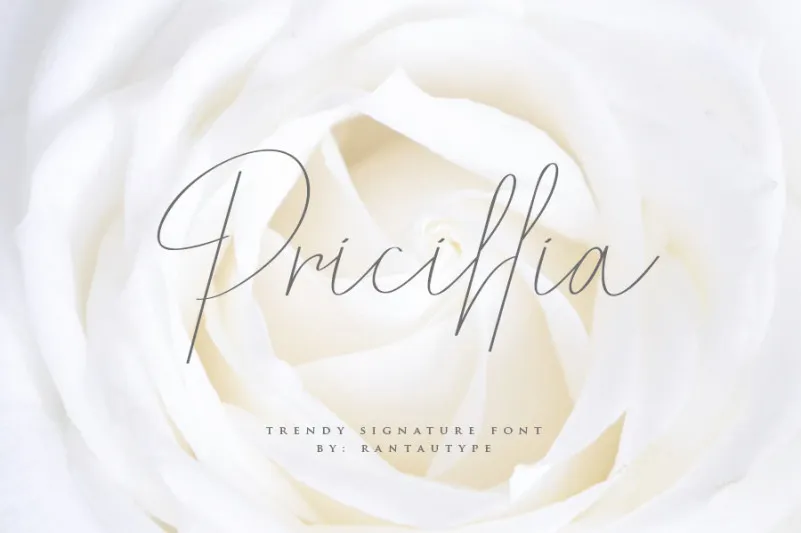
Pricillia Signature Font
A Pricillia Signature Font é uma escolha perfeita para quem busca adicionar elegância aos seus projetos digitais. Inspirada nos traços delicados e sofisticados das mulheres, essa fonte tem um estilo clássico que adiciona um toque natural a qualquer design. Ideal tanto para uso em headlines como logotipos ou rótulos de embalagens, ela se adequa perfeitamente para aplicar em designs variados, desde assinaturas e marcas até postagens no Instagram e capas de livros. Com seu charme elegante e sua personalidade sofisticada, Pricillia Signature Font é uma opção perfeita para designers que desejam dar um toque autêntico e refinado em seus trabalhos. É ideal para aquelas ocasiões especiais como aniversários ou bodas, bem como para estilizar roupas de moda ou t-shirts criativas. Este tipo font traz uma atmosfera fresca e moderna à sua criação sem deixar de manter o padrão elegante e sofisticado que tanto valorizamos no design gráfico atual.